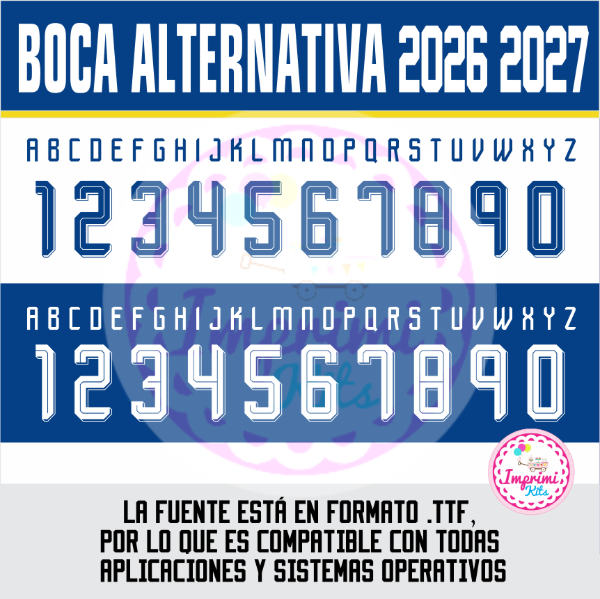
NUEVA! Tipografía Números Fuente Camisetas 2026 2027 BOCA JUNIORS ALTERNATIVA SEGUNDA EQUIPACIÓN
Tipografía Números Fuente NUEVAS EQUIPACIÓNES
Realizá todo tipo de creaciones con la tipografía utilizada actualmente en el club